Nel design, i dettagli fanno la differenza e uno degli elementi che può trasformare un progetto da ordinario a straordinario è la scelta del font.
Se stai lavorando a un progetto che ambisce ad essere esclusivo e raffinato, scegliere i migliori font eleganti sarà fondamentale per trasmettere un senso di classe e professionalità fin dalla prima occhiata. Tuttavia, selezionare il font giusto richiede attenzione: è essenziale bilanciare eleganza e leggibilità per garantire un risultato esteticamente piacevole e allo stesso tempo funzionale.
In questo articolo ti spiegheremo come scegliere il font più adatto alle specifiche del tuo progetto e ti forniremo una selezione dei migliori font eleganti da scaricare gratis.
Contesti di utilizzo dei Font Eleganti
I font eleganti sono estremamente versatili e possono rivelarsi utili in diversi ambiti creativi:
- Branding e Loghi: un font elegante rende immediatamente riconoscibile un marchio, trasmettendo un senso di lusso e professionalità. Un font elegante è indispensabile se stai lavorando, ad esempio, al brand di un’azienda di moda, di gioielli o di design.
- Materiale Pubblicitario: che si tratti di brochure, volantini o banner, un font elegante cattura l’attenzione e lascia una forte impressione, ideale per eventi esclusivi o prodotti di fascia alta.
- Inviti e Biglietti: per eventi speciali come matrimoni o celebrazioni, i font eleganti su inviti cartacei o digitali aggiungono un tocco di classe, anticipando l’atmosfera dell’evento stesso.
- Design di Siti Web: Anche i siti web traggono beneficio dall’uso di font eleganti, soprattutto se rappresentano aziende o brand di lusso, dove la tipografia gioca un ruolo centrale nell’identità visiva.
Caratteristiche dei Font Eleganti
I font eleganti presentano alcune caratteristiche distintive che li rendono ideali per progetti raffinati:
- Linee sottili: spesso caratterizzati da tratti delicati e leggeri, i font eleganti trasmettono sempre una sensazione di leggerezza, cura e precisione.
- Semplicità o sofisticatezza?: un font elegante può essere tanto minimalista quanto elaborato. Font semplici come i Sans Serif offrono eleganza attraverso la pulizia, mentre i font Script e Calligrafici, con curve e decori, aggiungono una raffinatezza più elaborata, ideale per occasioni formali.
- Elementi decorativi: Swashes, ligature e glifi sono elementi comuni nei font eleganti, soprattutto negli script, per aggiungere un tocco artistico a titoli o loghi. Caratteri di questo tipo sono decisamente meno appropriati per i testi in quanto, di solito, non garantiscono la miglior leggibilità.
Diversi tipi di Font Eleganti (e quando usarli)
I font eleganti possono essere di diversi stili tipografici: Script, Serif e Sans Serif. Vediamo di seguito quai sono le loro caratteristiche e in quali ambiti creativi utilizzarli.
Font Script e Calligrafici: eleganza, raffinatezza e creatività
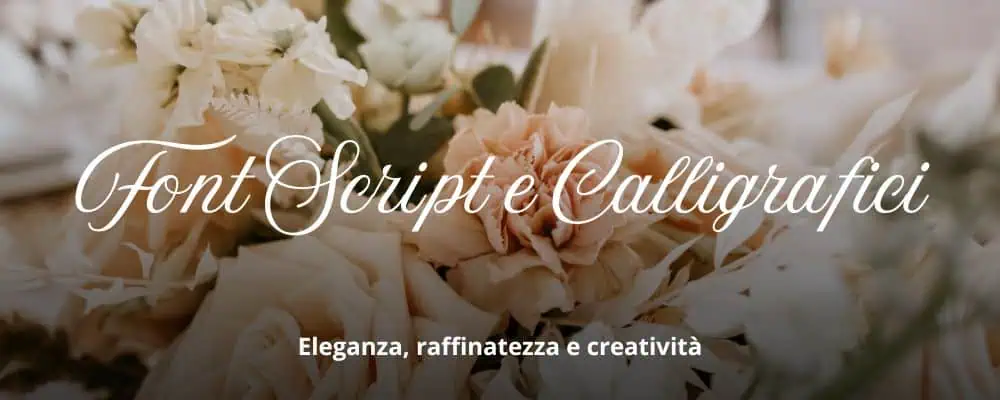
I font Script imitano la scrittura manuale, con linee fluide e curve decorative che riprendono lo stile della calligrafia. Perfetti per progetti creativi, possono dare un tocco personale e artistico. Si dividono in script “formali”, più simili ad una calligrafia ordinaria, e script “casual”, con un aspetto più marcatamente grafico e artistico.
Quando utilizzare un font Script:
- Inviti e partecipazioni a eventi formali (matrimoni, feste di laurea)
- Progetti di brand creativi (loghi e poster artistici)
Font Serif: tradizione, serietà e autorevolezza
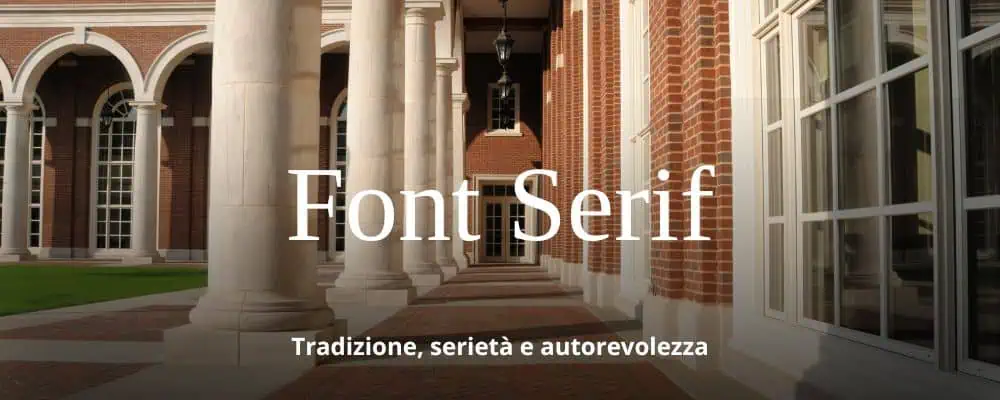
Il termine “Serif” si riferisce ai piccoli tratti decorativi che si trovano alle estremità delle lettere in alcuni font. Questi tratti, chiamati anche “grazie”, danno un aspetto più tradizionale e classico al testo.
Sono perfetti per materiali stampati come libri, riviste e cataloghi. Idonei tanto per i titoli quanto per i testi. Esempi noti di font Serif includono Times New Roman, Georgia e Garamond.
Quando utilizzare un font Serif:
- Documenti formali (legali o accademici)
- Progetti tipografici classici
- Progetti che vogliono trasmettere autorevolezza e serietà
Font Sans Serif: modernità, sobrietà e pulizia
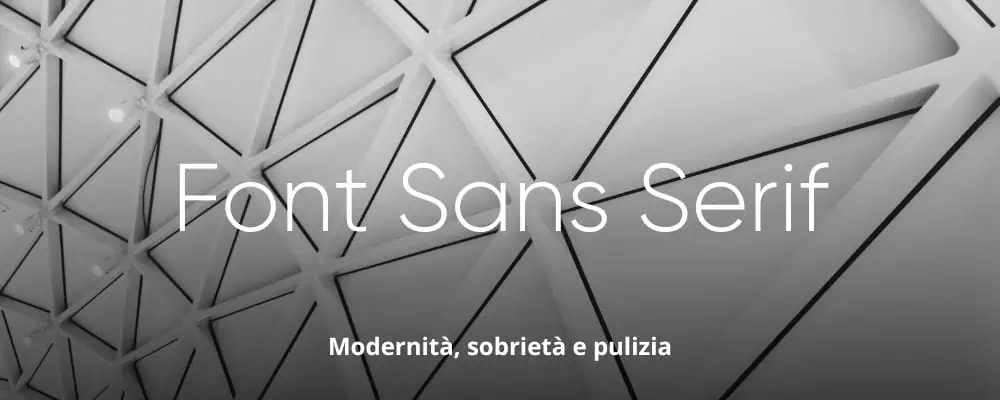
I font Sans Serif sono caratterizzati dall’assenza delle “grazie” (sans serif significa, appunto “senza grazie”), offrendo un design moderno e minimalista. Questi font funzionano particolarmente bene nei progetti digitali, dove la chiarezza su schermo è fondamentale e, solitamente, sono ottimi tanto per i titoli quanto per i testi. Esempi popolari di font Sans Serif sono Arial, Helvetica e Verdana.
Quando utilizzare un font Sans Serif:
- Progetti digitali (siti web, app, slide, video)
- Brand innovativi
- Progetti caratterizzati da linearità, semplicità e gusto minimale
In breve:
- Script: elegante e decorativo, ideale per loghi e titoli brevi in progetti artistici ed eventi speciali.
- Serif: classico e formale, adatto a testi lunghi e materiali stampati.
Con oltre 100 caratteri, tra cui lettere minuscole, numeri, punteggiatura e alcuni caratteri speciali, Code è una scelta ideale per progetti di branding, poster e design digitali.
Il suo stile geometrico e contemporaneo lo rende popolare per chi cerca un look elegante e chiaro, perfetto per dare un’impronta moderna e professionale ai progetti.